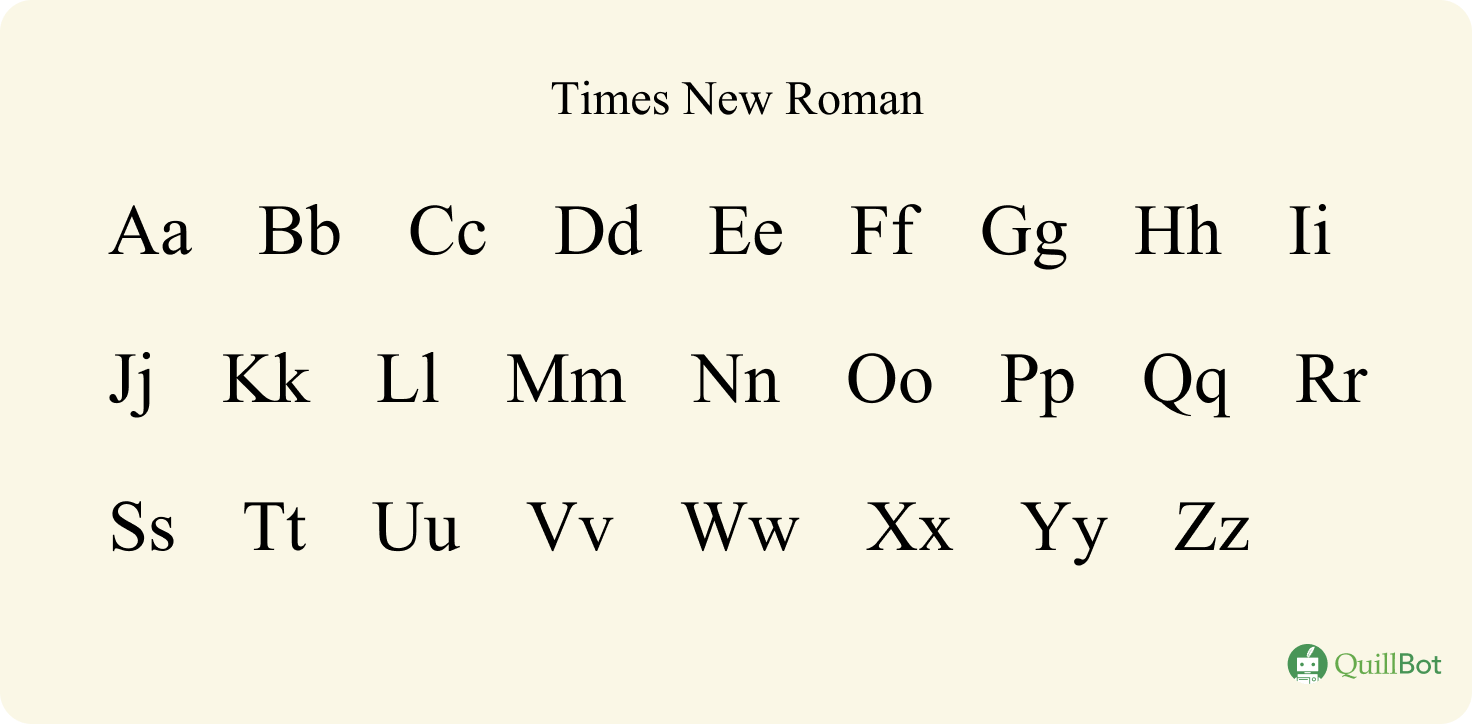
Times New Roman, la police qui traverse les époques
Lorsque l’on pense « police d’écriture », quelques noms nous viennent immédiatement en tête, souvent les mêmes au demeurant : Arial, Comic Sans MS, Helvetica, Tahoma… et, bien sûr, Times New Roman.
Times New Roman : fiche d’identité
• Année de création : 1931
• Pays de création : Angleterre
• Créateurs : Stanley Morison & Victor Lardent
• Commercialisation : Par Monotype Corporation
• Type de police : Classique, historique
• Type d’empattement : Avec empattement (serif en anglais)
• Classification Vox-Atypi : Réale
• Popularité : +++ (utilisée essentiellement pour l’édition de livres)
• Image véhiculée : Classique, professionnelle, traditionnelle, formelle.
• Point d’attention particulier : Police des communications officielles et diplomatiques américaines.
Créée à l’origine pour la presse (on a tous en tête l’image d’un article de journal en anglais rédigé en Times New Roman), elle est devenue virale auprès du grand public à partir des années 1990, grâce à son intégration sur Windows, et notamment en tant que police par défaut du logiciel de traitement de texte Word.
Ce que l’on sait moins, c’est que Times New Roman doit aussi son plébiscite populaire à la quantité moindre qu’elle consomme en impression… Qui a dit qu’il n’y avait pas de petites économies ?
Mettre en page vos écrits avec Times New Roman avant de les partager leur donnera sans conteste une aura de sérieux, d’élégance et d’autorité.
Police Times New Roman : histoire et commercialisation
Times New Roman s’est révélée pour la première fois aux yeux du grand public le 3 octobre 1932.
Il s’agit du jour où le journal The Times (communément appelé « le Times » en français) a sorti sa première édition imprimée en Times New Roman, une police de caractères spécialement créée sur demande de la direction du quotidien.
Mais revenons quelques années plus tôt.
En 1929, le journal britannique The Times, désireux de changer de police pour moderniser son image, gagner en lisibilité et économiser du budget à l’impression (quoi de plus normal au moment du fameux krach boursier de 1929 et des prémices de la Grande Dépression qui en découlera…), mandate Stanley Morison.
Conseiller typographique employé par la Monotype Corporation, Morison leur paraît être l’homme de la situation.
Stanley Morison, un choix symbolique sans le savoir
Savoir que c’est à Stanley Morison que le Times a fait appel ne manque pas de sel lorsqu’on sait que c’est justement grâce au Times que celui-ci a embrassé la carrière de typographe…
En septembre 1912, Stanley, alors âgé de 23 ans, achète un exemplaire du Times du jour. Jusqu’ici, rien de bien pittoresque… Mais la donne change lorsqu’il y découvre, coincé entre deux pages, un supplément sur le monde de l’imprimerie. Il lit la brochure, ou plutôt, il la dévore avidement.
Il n’en faudra pas plus à ce passionné de théologie et de calligraphie pour décider d’embrasser définitivement la voie de la typographie. Morison a trouvé sa vocation grâce au Times, et le créateur de caractères a pu lui rendre la pareille presque deux décennies plus tard.
Ainsi, la boucle est magnifiquement bouclée…
Avec le concours du dessinateur Victor Lardent, Morison conçoit une police qui optimise comme aucune autre l’espace imprimé tout en permettant des économies d’encre considérables. Cerise sur la typo, leur création peut se targuer d’avoir fière allure ; de faire « sérieux », mais pas guindé.
En partie basée sur deux polices déjà existantes (Plantin et Perpetua), Times New Roman voit le jour en 1931 !
Il faudra attendre fin 1933, soit un an après sa première sortie dans le journal The Times, pour que son design soit publié à des fins de vente commerciale au public.
La police Times New Roman connaîtra une refonte historique en 2006, toujours commandée par le quotidien qui fut à l’origine de sa première mouture. Les proportions et les détails diffèrent légèrement, mais pas de quoi sauter aux yeux des foules non initiées.
Times New Roman : un traitement VIP chez Google
Si vous saisissez la requête « Times New Roman » dans la barre de recherche Google, sachez que la page de résultats s’affichera entièrement en Times New Roman, et non avec la police native habituelle, Google Sans.